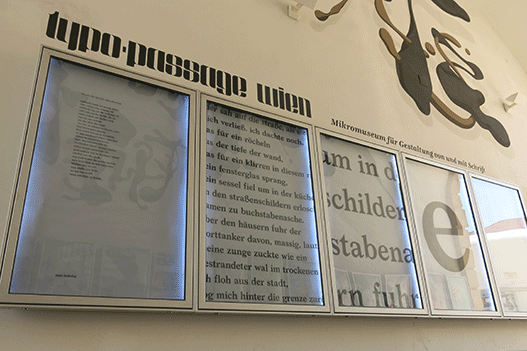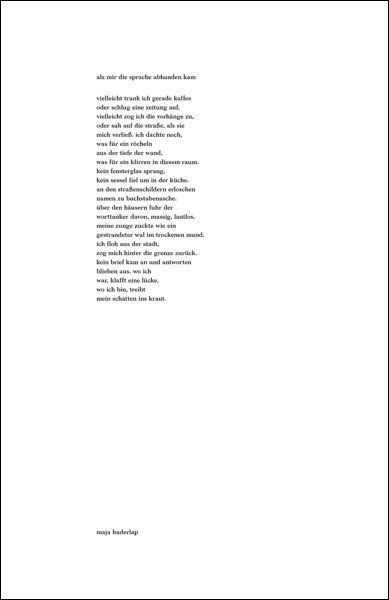
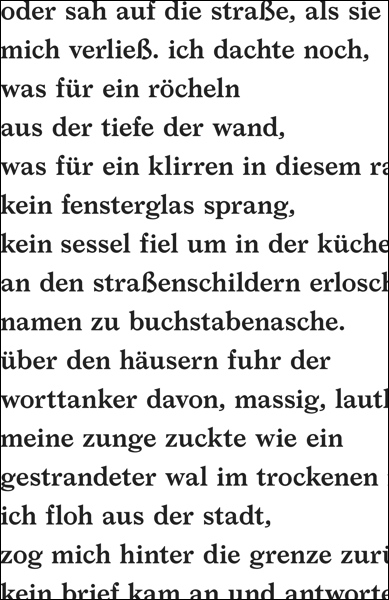
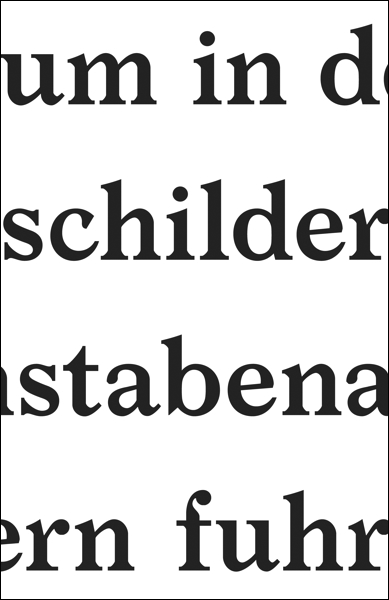
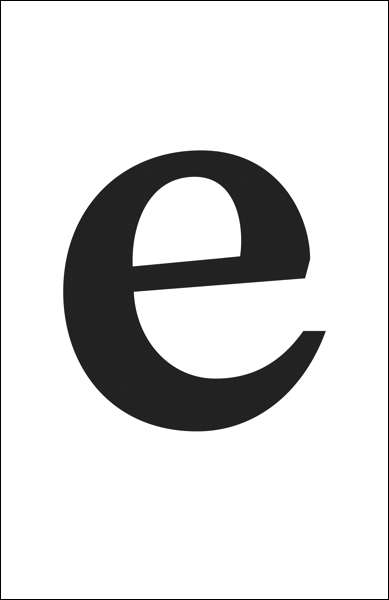
Text
Ein Gedicht aus dem Band langer transit, erschienen 2014 im Wallstein Verlag. Maja Haderlap schreibt Prosa, Gedichte und Essays auf Deutsch und Slowenisch. Ihr Roman Engel des Vergessens (2011) wurde unter anderem mit dem Ingeborg-Bachmann-Preis und dem Rauriser Literatur- preis ausgezeichnet und in viele Sprachen übersetzt.
Typografie
Die Schrift Larish Neue von Radim Pesko basiert auf Schriftentwürfen Rudolf von Larischs aus dem frühen 20. Jahrhundert und wurde 2006 für das visuelle Erscheinungsbild der Wiener Secession entwickelt, welches nur sehr kurz im Einsatz war. www.radimpesko.com
Rudolf von Larisch (1856–1934) war ein österreichischer Schriftgestalter und Hochschullehrer. In seinen Büchern und Essays propagierte er die Verwendung der »Lateinschrift« (Vorläuferin der Groteskschrift) und kritisierte die damals verbreitete Frakturschrift. Rudolf von Larisch war ein früher Verfechter der Kleinschreibung, begründet durch die historische Entwicklung der Versalien (Majuskeln), die auf Anordnung Karls des Großen mit dem auf der Handschrift basierenden Minuskel-Alphabet vermischt wurden. »Schrift kommt vom Schreiben«, sagte Rudolf von Larisch und meinte damit den natürlichen Schreibfluss der Handschrift, der als Basis unserer Schrift gilt. Die Großbuchstaben des heutigen deutschen Alphabets sind streng genommen visuelle »Fremdkörper« in der Sprache. Ihre Formen beruhen nicht auf dem natürlichen Schwung der Hand, sondern auf der mechanischen Bearbeitung von Stein mit Hammer und Meißel. Wie zwei verschiedene Sprachen wurden zwei unterschiedliche Alphabete vereint, die nie ganz miteinander verschmolzen. Um Sprache und Übersetzen geht es auch in Maja Haderlaps Gedicht als mir die sprache abhanden kam. Es sind die zentralen Themen in Haderlaps Literatur, die sie bis heute begleiten.
Gestaltung